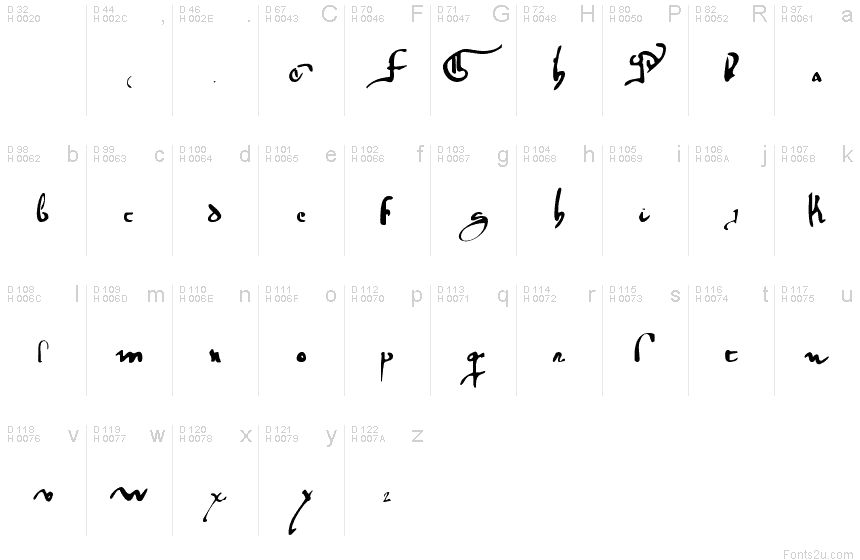
Gotische Minuskel 1269 Pw, creata da Paulo W, è un font gotico calligrafico gratuito. Parte della famiglia Gotische, unisce tratti densi e carichi d'inchiostro a curve sciolte e dinamiche, facendo sembrare ogni parola tracciata velocemente con un pennello. Le lettere si intrecciano con un movimento drammatico, conferendo alla vostra tipografia un'intensità grezza e artigianale, piuttosto che un look calligrafico troppo studiato.
Usate Gotische Minuskel 1269 Pw per infondere questa energia oscura e fluida a loghi di band, copertine di libri fantasy o occulti, titoli di poster, packaging, tatuaggi o grafiche audaci per i social media. I tratti spessi e continui risaltano particolarmente nei grandi formati, dove ogni torsione e tratto può respirare. Abbinate questo font gratuito a un sans serif geometrico pulito per i testi piccoli: manterrete la leggibilità lasciando che sia lo script a rubare la scena.